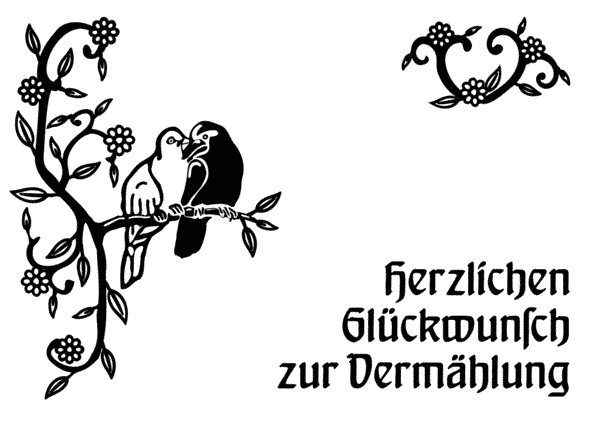
Bayrische Hochzeit
ich bin auf der Suche nach einer Schrift für die Ausstattung einer betont bayrischen Hochzeit (Kleidung, Essen, …). Es braucht nicht unbedingt mehrere Schnitte, gut wär es aber schon.
An kommerziellen Schriften hab ich alles zur Verfügung, was bei den CS von 2.3 bis 5 beigelegt war, alle Windows- und Mac-Systemschriften, dazu noch ein paar andere, und natürlich alles was nichts kostet. Falls es nicht zu teuer wird und sie mir so gut gefällt, dass ich sie später auch noch verwenden will, könnte ich auch ein bisschen Geld ausgeben.
Verwendet werden soll sie für Einladungen, Platzkarten usw., wobei sie natürlich auf Papier gedruckt wird, aber evtl. auch teilweise in Holz gebrannt (steht noch nicht fest).
Ich hab mal in meiner Sammlung von gebrochenen Schriften gesucht und bin bei „Fraenkisch“ und „Behrensschrift“ von Dieter Steffmann gelandet. Die sind beide auch für Laien leicht zu lesen und nicht so kantig. ſ und die üblichen Ligaturen wären natürlich gut (ob ich das ſ einsetzen darf liegt nicht an mir).
Ich will das ganze aber nicht auf Gebrochene einschränken, das war nur mein erster Gedanke. Möglicherweise nehm ich auch zwei Schriften, davon eine für Displayzwecke, eine für Fließtext, wobei keine wirklich langen Texte vorkommen.
Ich hab mal in meiner Sammlung von gebrochenen Schriften gesucht und bin bei „Fraenkisch“ und „Behrensschrift“ von Dieter Steffmann gelandet. Die sind beide auch für Laien leicht zu lesen und nicht so kantig.
Die Fraenkisch finde ich zum Thema Hochzeit ziemlich passend. Sie ist allerdings recht mager. Mit Bayern verbinde ich gerade mehr kantige, kräftige Formen, wie beispielsweise in der Trump:
– oder in der Koch-Fraktur, deren magerer Schnitt bei Helzel kostenlos erhältlich ist:
Wenn Du aber eher eine feinere Schrift verwenden möchtest, wäre die Fränkisch sicher keine schlechte Wahl. Ich würde aber das B ggf. etwas überarbeiten, das könnte nämlich leicht mit dem R verwechselt werden.
Ich hab jetzt mal einen Entwurf hauptsächlich mit der Fränkisch gemacht. Zusätzlich, räumlich getrennt vom restlichen Text, die Münchner Fraktur für die Wörter „G’heirat werd’“.
Das mit dem B ist wirklich ein bisschen unpraktisch, weil der Bräutigam zwei davon im Namen hat. Aber ich kann die Schrift auch nicht bearbeiten.
Möglicherweise heute noch mach ich einen kleinen Testdruck. Falls der zeigt, dass mein Konzept soweit funktioniert, zeig ich euch vllt. den momentanen Stand (muss aber dann persönliche Daten rausnehmen).
Das ganze ist jetzt eine Klappkarte (wie ein Fensterladen mit ungleich breiten Flügeln)
Die Außenseite:
Die Innenseite:
Was mir ganz allgemein auffällt: Ich würde die Apostrophen bei dad’n, frei’n usw. weglassen. Der Text soll die gesprochene Sprache nachahmen, und mia in Bayern mia redma so wias Mai gwachsn is. Verschlucka deama eh d Hoiftn, da braugst koa Zeichn neda.
Dem "freit" gehört noch ein g vorangestellt, also "gfreit" (oder g’freit, wenn du die Apostrophe belassen willst.) Hier gibt’s noch ein paar Grundlagen.
Hätt ich auch so gesehen, ist aber nicht meine Hochzeit, daher hab ich da nur begrenzt Einfluss. :-? ;)
bin ich eigentlich der Einzige der bei diesem Thema an eine Rotunda (Rundgotische) oder sowas wie die Bauernschrift oder Hohenzollern (entfernt ähnlich der Behrensschrift, siehe Beispiel unten) auf TypOasis gedacht hat? Das meiste findet man als freie Ware auf TypOasis:
Gerade die Rotunda bietet sich doch für die nördlichste aller italienischen Provinzen an? Und sie für Frakturentwöhnte ist wesentlich leichter zu lesen als eine Textura oder Fraktur. Wo ist da mein Denkfehler?
Das sieht aus wie eine Trauerkarte. Für Bayern ist die Schrift einfach nicht typisch.
Ich finde die Fraenkisch paßt ausgezeichnet! Auch der Spruch ist toll! :-P
Aber die Form des B stört wirklich. Als kleines Hochzeitsgeschenk hab ich deshalb auf die Schnelle mal was gebastelt:
Und noch was: Was ist dieses kleine Ding unter dem Herz? Das würde ich eher weglassen.
Das sieht aus wie eine Trauerkarte.
Da konnte ich meine Assoziationen wohl nicht unterdrücken? Die Karte ging übrigens auch in den katholischen Balkan. Allerdings nicht Bayern, sondern Kroatien.
;-)
Für Bayern ist die Schrift einfach nicht typisch.
Klar, daher der Hinweis auf die Rundgotischen. Aber die gebrochenen Schriften mit den starken Strichdickeunterschieden (wie Old English und Co) passen IMHO auch nicht so richtig. Die wirken auf mich zu preußisch-streng.
Ich finde die Fraenkisch paßt ausgezeichnet! Auch der Spruch ist toll! :-P
Welcher Spruch? „G’heirat werd“? Für eine Hochzeitseinladung besser geeignet als die prototypische bairische Liebeserklärung „Zwider warst ma ned“* ;-)
Aber die Form des B stört wirklich. Als kleines Hochzeitsgeschenk hab ich deshalb auf die Schnelle mal was gebastelt
Dafür ist es jetzt leider zu spät, die Karten sind schon gedruckt.
Was ist dieses kleine Ding unter dem Herz? Das würde ich eher weglassen.
Mein „Ich hab’s gemacht“-Signet 8-)